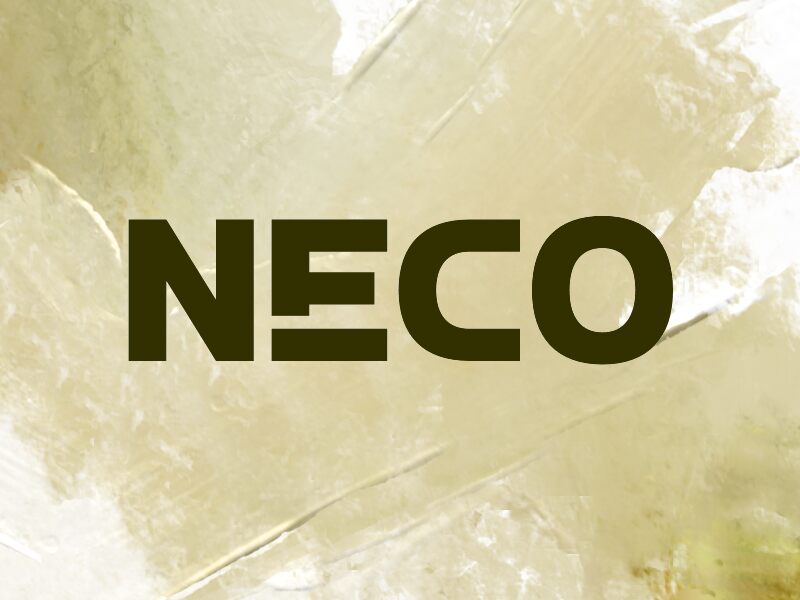
Neco di Wep è un font display futuristico gratuito, caratterizzato da uno stile tecnologico smussato e arrotondato. Le lettere combinano angoli morbidi e forme piene e incise, facendo sì che la N larga e le compatte e, c e o ricordino la segnaletica di un brand del futuro prossimo, piuttosto che un semplice sans serif neutro.
È perfetto per loghi di videogiochi, copertine musicali, packaging tecnologici, titoli di poster e cartelli dove le parole brevi necessitano di un tono solido e sintetico. Essendo un font gratuito, Neco è ideale anche per splash screen di app e grafiche per streaming, soprattutto quando si desidera un lettering massiccio, semplice e leggermente robotico, senza scivolare nei cliché dei giochi arcade rétro.
Presentazione e campione visivo del carattere Neco